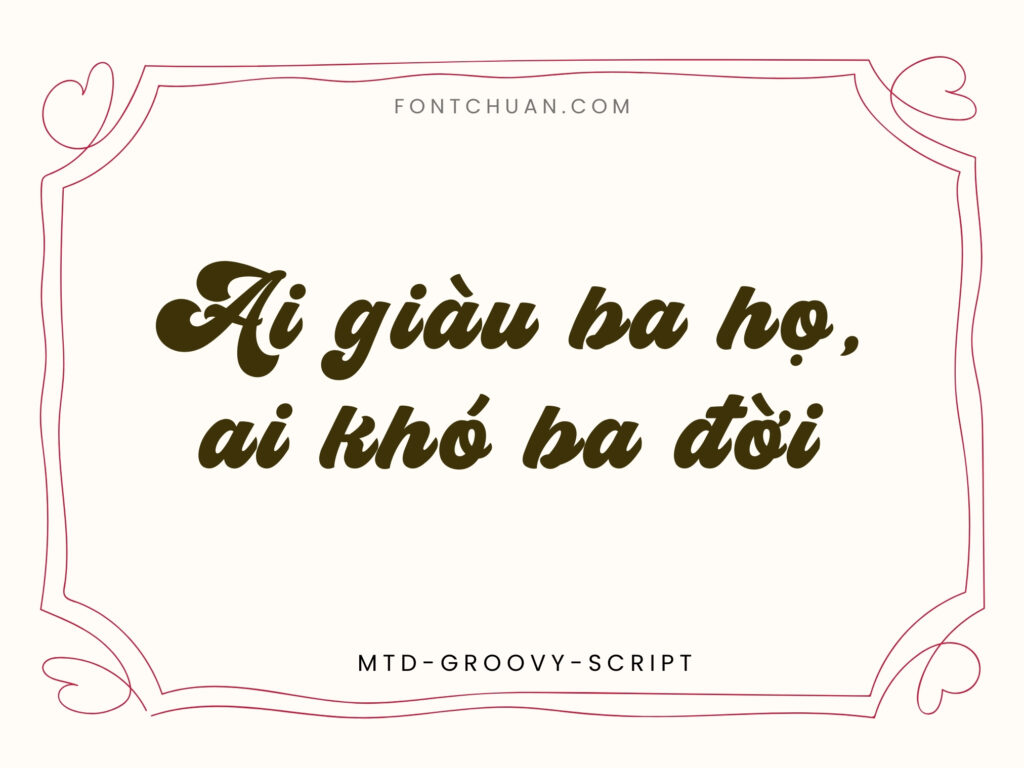
Font MTD Groovy Script Việt Hóa
Tác giả Font: Hendra Pratama
Font MTD Groovy Script là một phông chữ script mang phong cách retro, được thiết kế bởi Hendra Pratama và phát hành trên FontBundles. Font đã được Việt hóa bởi Mộc Hạ, hỗ trợ tiếng Việt và hơn 90 ngôn ngữ khác, giúp mở rộng khả năng ứng dụng trong các thiết kế đa ngôn ngữ. Đây là một trong những phông chữ được cộng đồng thiết kế đánh giá cao và ứng dụng trong nhiều dự án sáng tạo, đáp ứng nhu cầu đa dạng của người dùng.
MTD Groovy Script nổi bật với các đường nét mềm mại, uyển chuyển và mang đến cảm giác hoài cổ nhưng vẫn hiện đại. Font rất phù hợp cho các thiết kế logo, tiêu đề, bao bì sản phẩm, thiệp mời và các ấn phẩm đòi hỏi sự sáng tạo và cá nhân hóa. Các ngành nghề phù hợp bao gồm quảng cáo, giáo dục, công nghệ, thiệp cưới và ảnh cưới. Font này cũng lý tưởng cho các sự kiện như Tết, Giáng sinh, Valentine và các lễ hội khác.